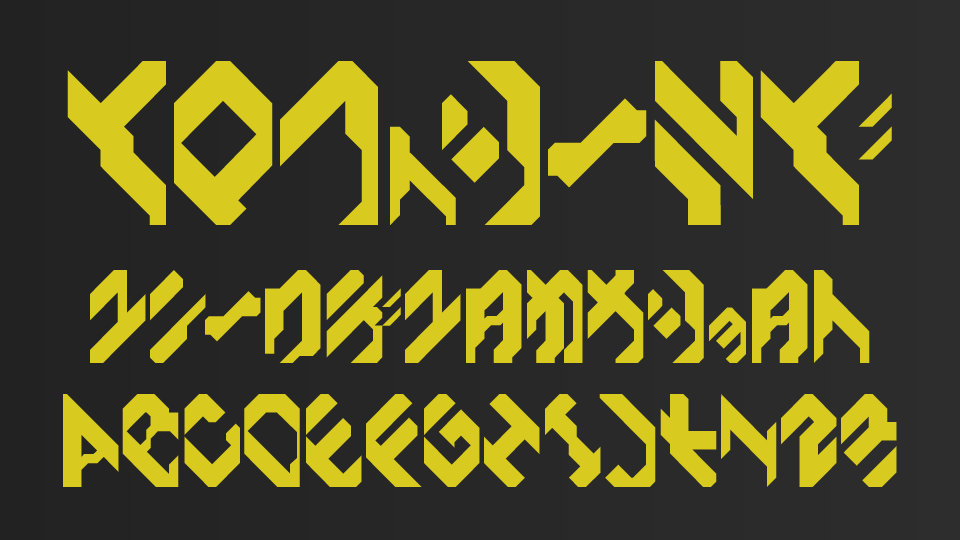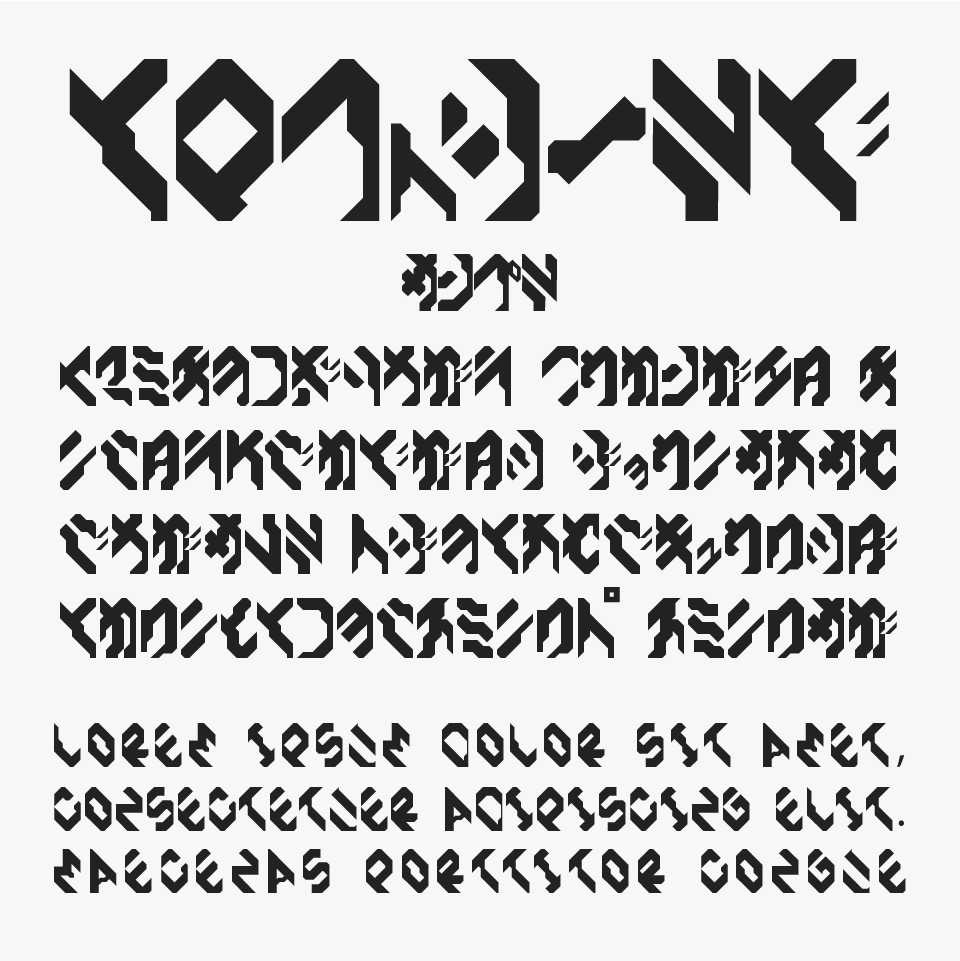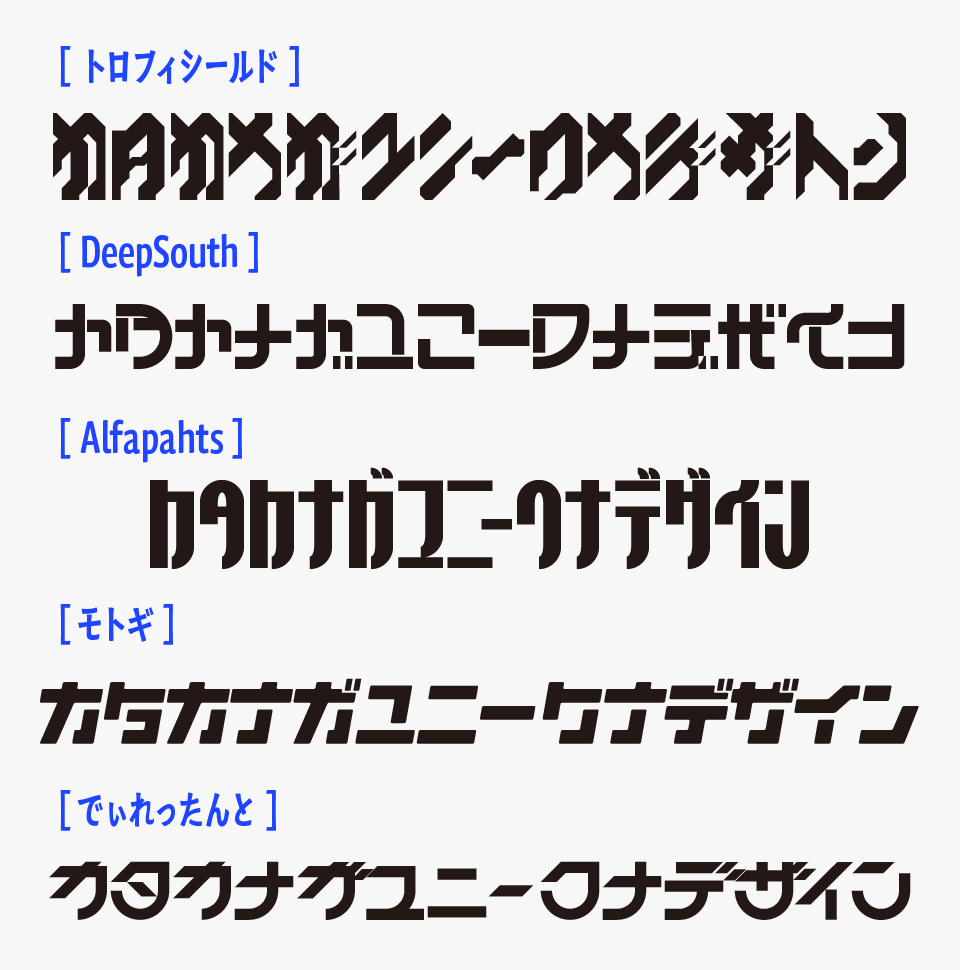
トロフィシールド
トロフィシールドフォントは、斜め45度の直線的なパーツを組み合わせて構成された、近未来的なデザインのカタカナフォントです。
文字の一部が分割されていたり、鋭く斜めにカットされていたりすることで、デジタル信号や機械装甲、近未来兵器のような印象を感じられるフォントです。エッジの効いたデザインながら全体のバランスは丁寧に整理されており、力強さと洗練された雰囲気を両立しているところが魅力のデザインです。
また、日本語だけでなくアルファベットも同じ世界観で設計されているため、和文・欧文を組み合わせても違和感がなく、統一感のあるビジュアルを作りやすいところも大きな特徴です。
eスポーツやSF作品、サイバー系ビジュアル、テクノロジー企業のロゴ、ゲームタイトルなどとも相性が良く、未来都市やデジタル空間を思わせるスタイリッシュな世界観を演出できるフォントとなっています。
トロフィシールドフォントを、ほかのSFっぽい雰囲気でユニークなスタイルを持つカタカナフォントと比較してみると、機械的な力強さと洗練された未来感のバランスが特に魅力のフォントです。
比較フォントは、「DeepSouth」「Alfapahts」「モトギ」「でぃれったんと」と使用していますが、どれもユニークなフォルムをしたデザインフォントなので、ぜひあわせてチェックしてみてください。